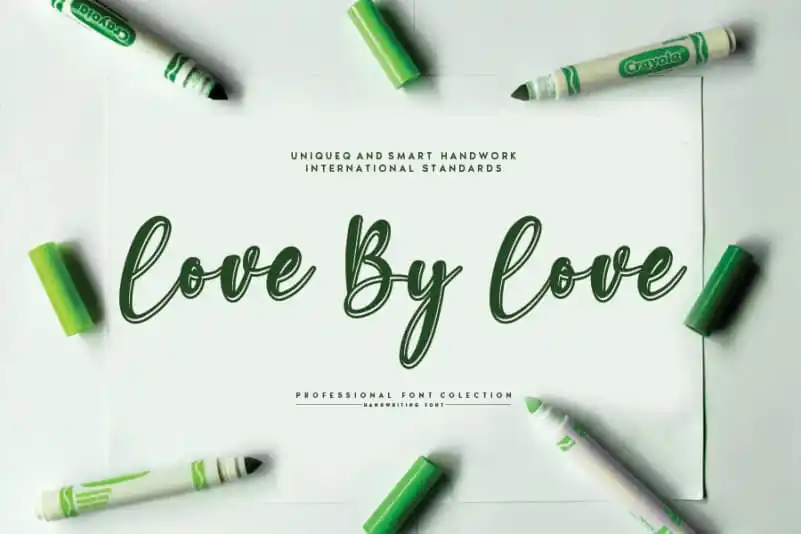
Love By Love Script Font – Fonte Grátis
Love By Love Script Font
A fonte “Love By Love Script Font” é uma elegante escolha para aqueles que buscam um toque sofisticado em seus projetos digitais sem perder a frescura atual. Desenhada pelo designer andikastudio, essa fonte escrita à mão transmite ao mesmo tempo charme clássico e modernidade renovada. Suas linhas fluidas e sua fidelidade às influências da calligrafia dão-lhe um charme próprio, ideal para textos de amor e afeto. Esta font é perfeita para aqueles que buscam uma alternativa à escrita tradicional, oferecendo um toque pessoal em qualquer projeto. Adquira agora a “Love By Love Script Font” e faça seu próximo trabalho realmente brilhar.